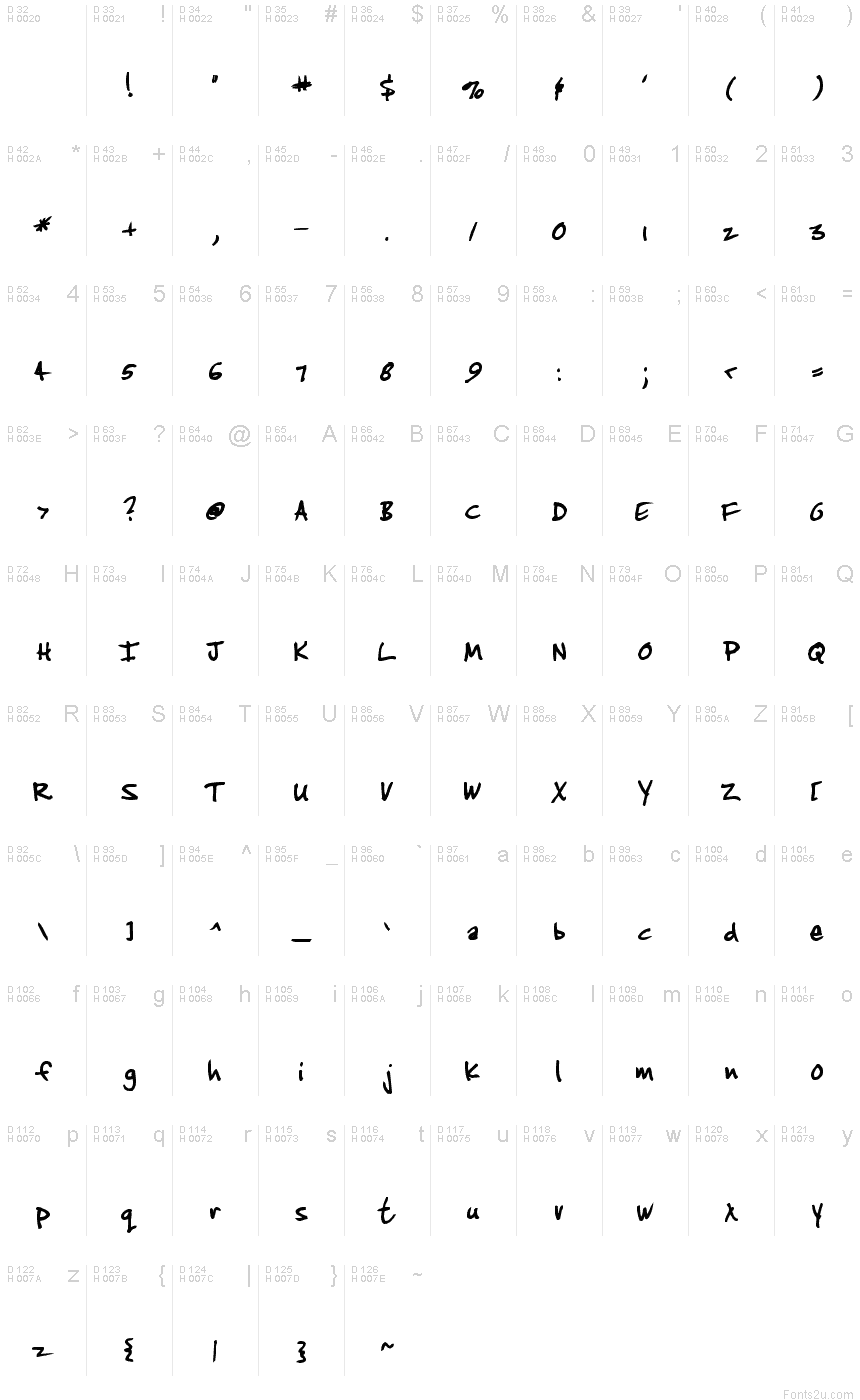
Krój Jenkins v2.0 Thik od Font'a'licious Fonts to darmowy, odręczny font. Jego masywne, nasycone tuszem kształty sprawiają wrażenie, jakby każdą literę poprawiono dwukrotnie grubym markerem, co nadaje tekstowi śmiałą, malarską energię. Litery są lekko chwiejne, co dodaje im ludzkiego, figlarnego charakteru, a ciasne odstępy sprawiają, że słowa czytają się jak wyraźne, uderzeniowe formy, a nie rozmyte bazgroły.
Używając Jenkins v2.0 Thik, nadasz zinom, plakatom koncertowym, projektom naklejek, okładkom książek dla dzieci, postom w social mediach i zabawnym opakowaniom wyrazisty charakter DIY, który pozostaje czytelny na pierwszy rzut oka. Ten darmowy font najlepiej sprawdza się w dużych rozmiarach, gdzie jego obłe krzywizny i surowe krawędzie naprawdę przyciągają wzrok. Aby uzyskać zbalansowany efekt, połącz go z czystym, wąskim bezszeryfowym krojem w tekście głównym, co zrównoważy jego masywną i ekspresyjną osobowość.